Une nouvelle grammaire visuelle.
L’agence Graphéine a livré une refonte ambitieuse de l’identité visuelle du Mont-Saint-Michel, confiée par l’Établissement Public National nouvellement créé pour coordonner la gestion du site et de sa baie, inscrite au patrimoine mondial de l’Unesco et attirant plus de 2,5 millions de visiteurs par an.
L’objectif affiché du projet était double : projeter l’image du Mont dans la modernité tout en construisant une marque cohérente, protégeable et accessible, dépassant les représentations stéréotypées habituelles de la silhouette du rocher et de son abbaye ; un enjeu stratégique pour un territoire partagé entre multiples acteurs publics et privés.
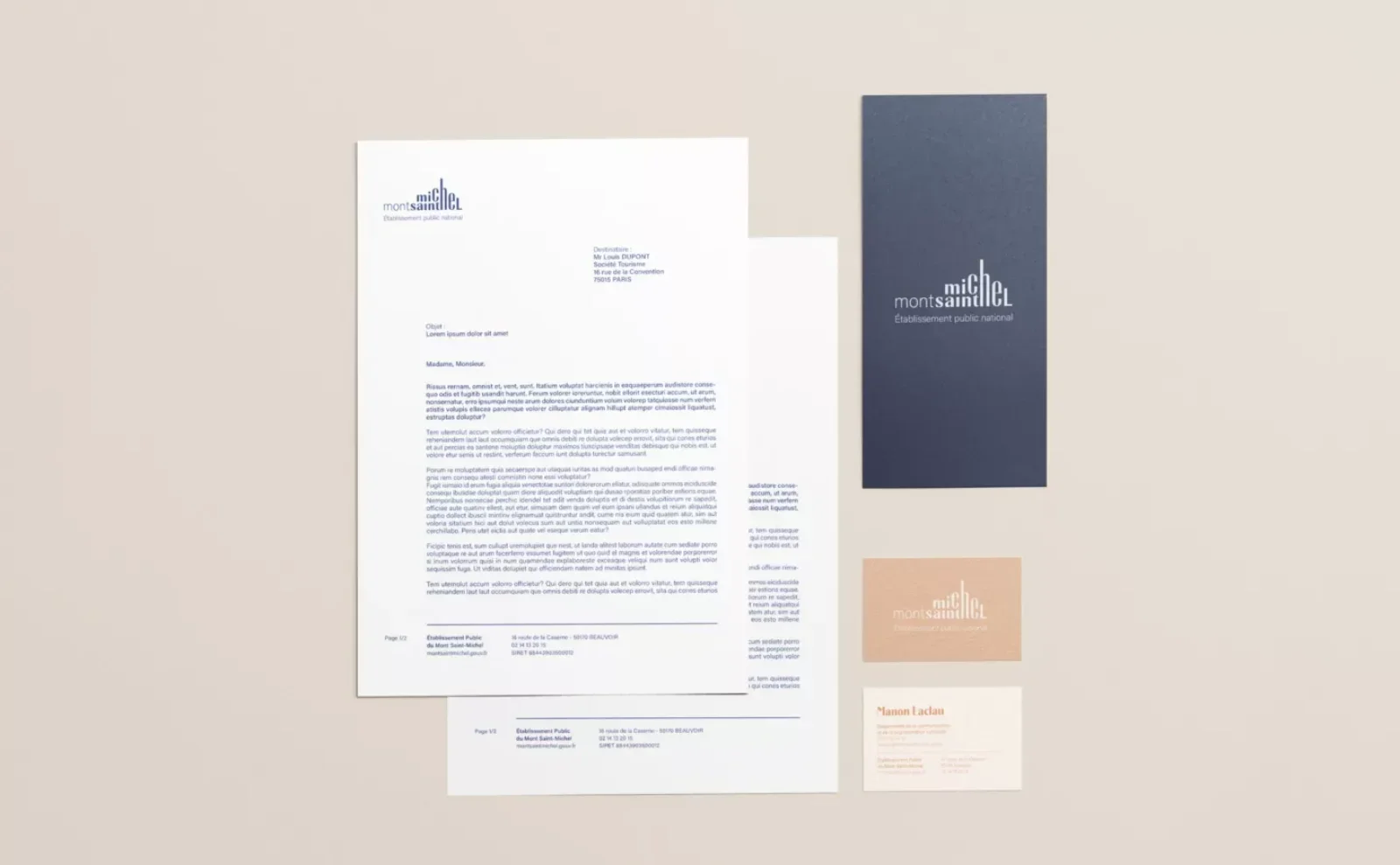
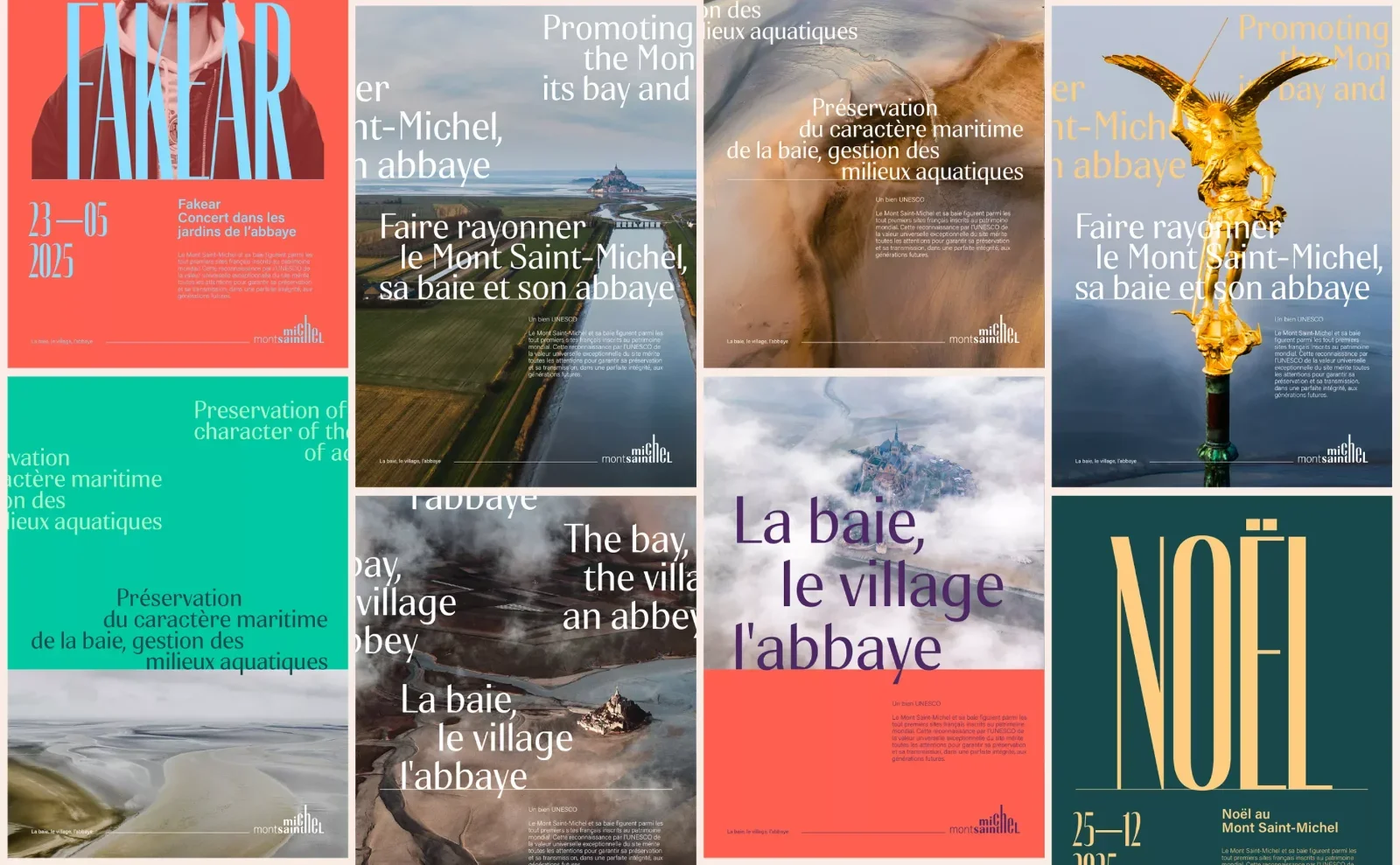
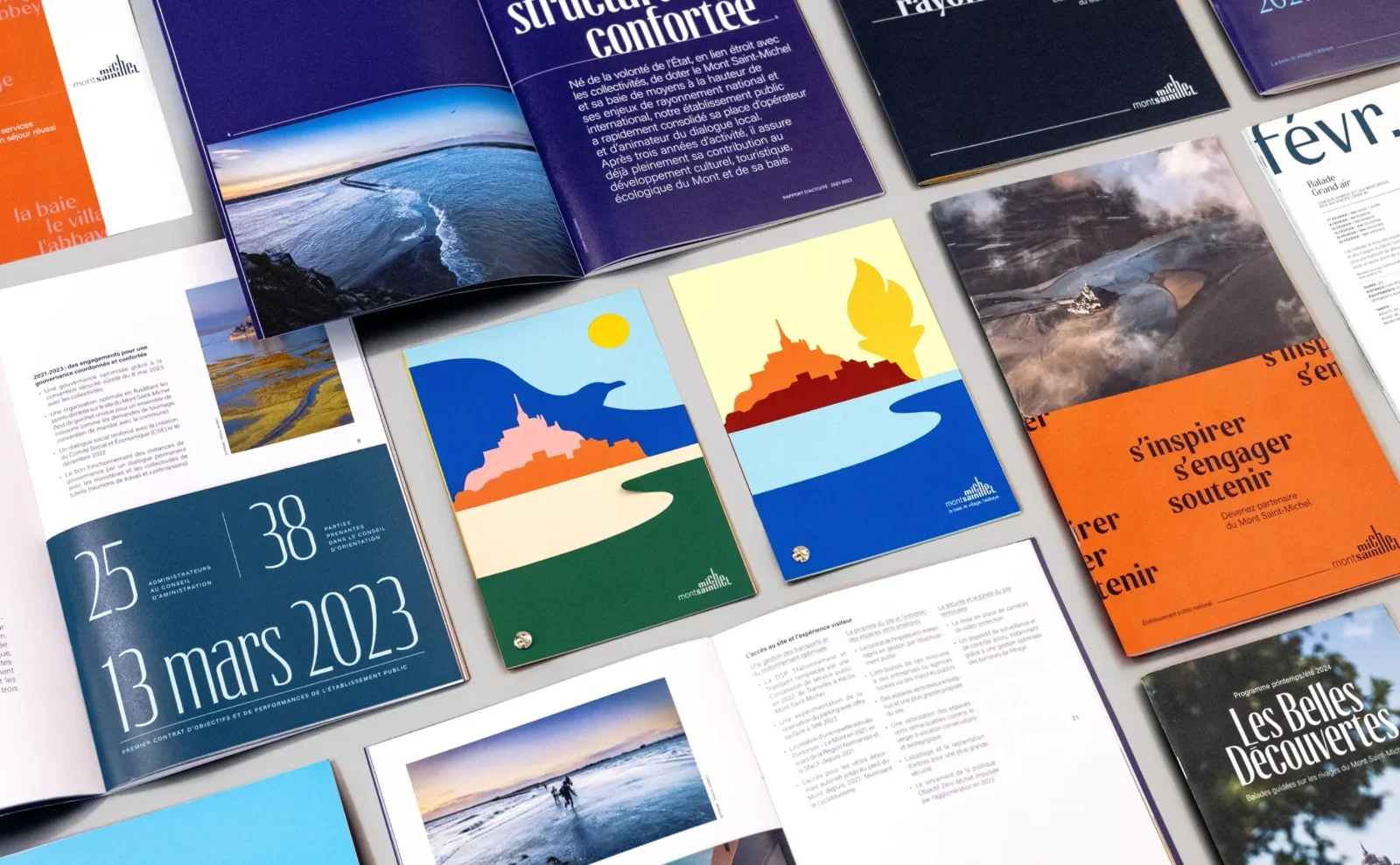
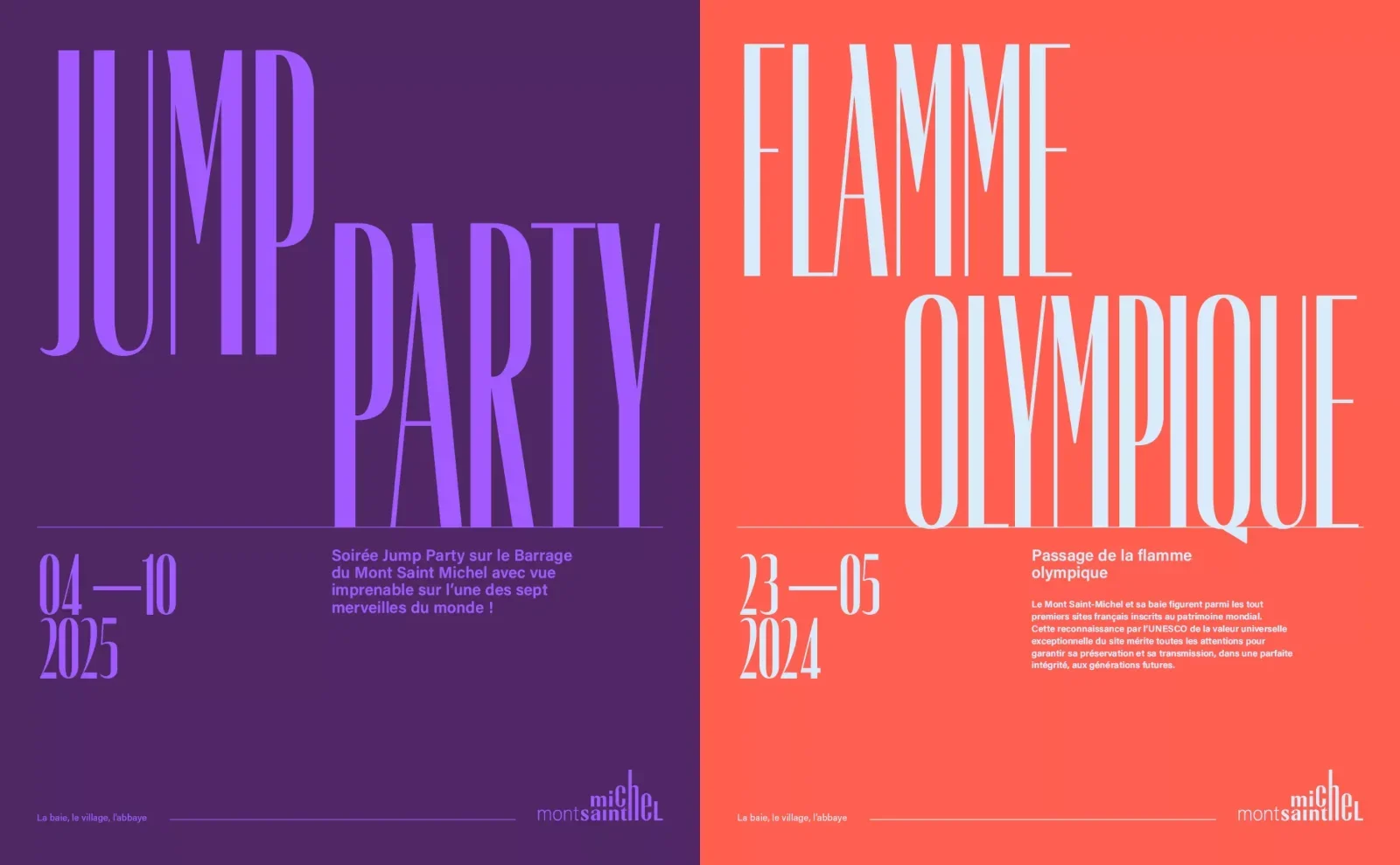
Plutôt que de se résoudre à une représentation figurative attendue, Graphéine a élaboré une identité centrée sur un typogramme singulier et une typographie originale développée avec la fonderie Blaze Type. Inspirée des écritures gothiques médiévales présentes dans les manuscrits du Mont-Saint-Michel, cette création typographique explore l’élévation verticale du lieu et ses caractéristiques architecturales, avec une finesse et une puissance visuelle servant à la fois l’esthétique et la lecturabilité. Cette démarche intègre autant l’héritage historique du site qu’une volonté de contemporanéité dans le design.
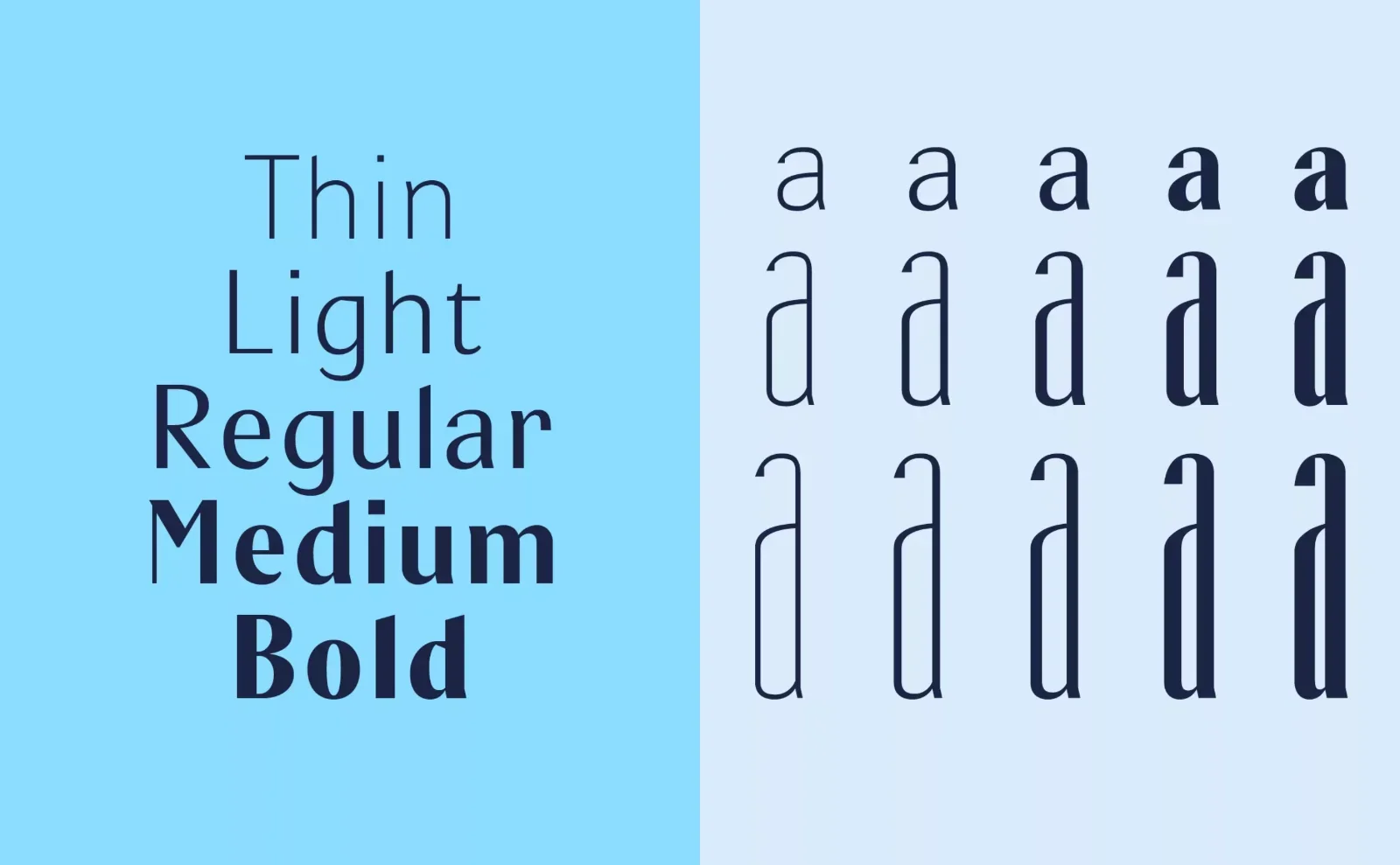
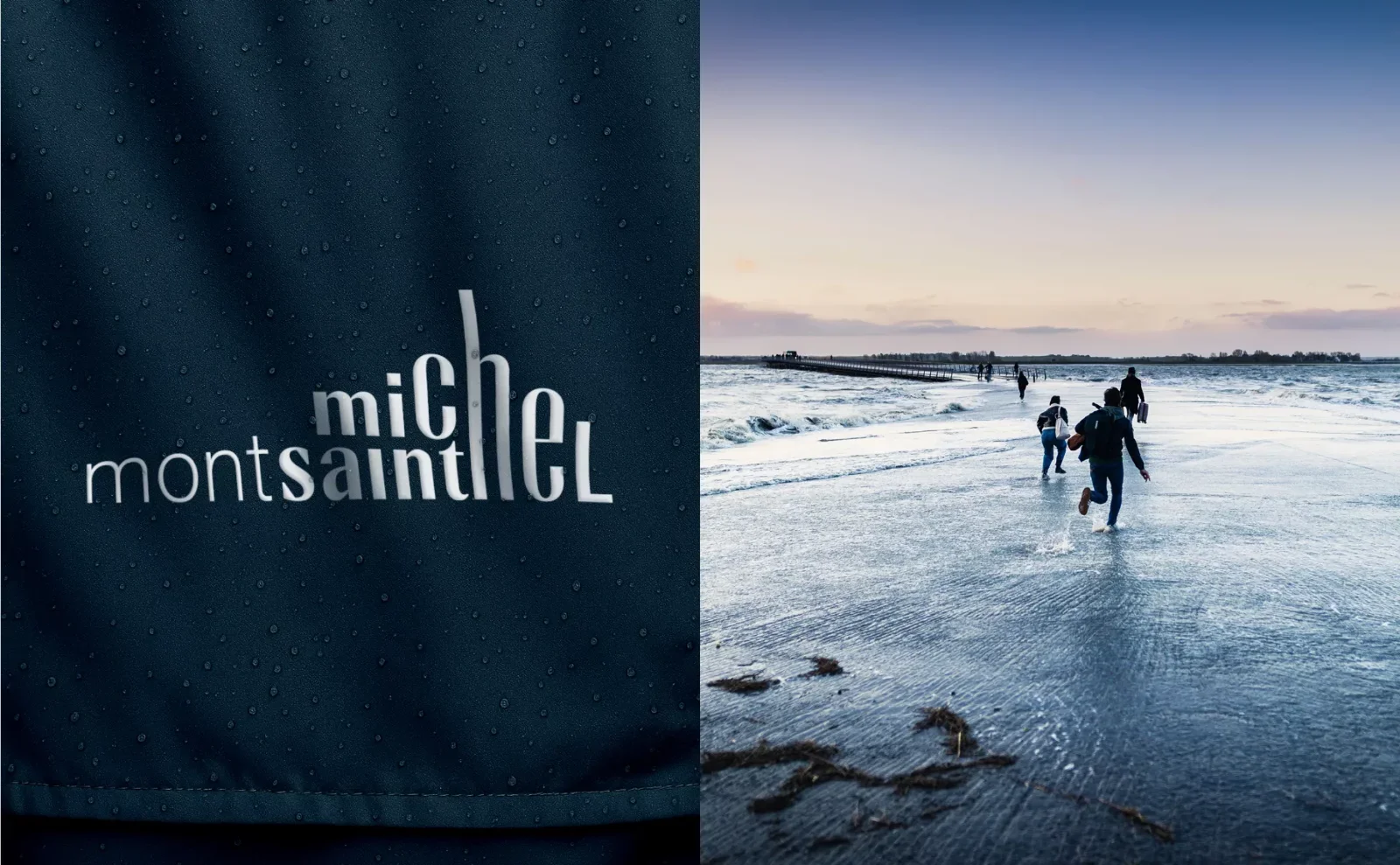
L’identité se déploie également à travers un univers visuel tiré des couleurs et des paysages de la baie, avec des teintes oscillant entre douceur naturelle et vibrance événementielle, ainsi qu’un système graphique qui élargit la perception du Mont à l’horizon de sa baie. L’approche iconographique, aérienne et contemplative, vise à refléter le caractère naturel et protégé du territoire tout en offrant une base modulable pour les actions institutionnelles et culturelles portées par l’Établissement Public.
L’histoire ne dit pas s’ils ont résolu le débat : Normand ou Breton le Mont Saint Michel ? Quoi qu’il en soit, il existe bel et bien, n’en déplaisent à certains qui le pensent généré par intelligence artificielle…